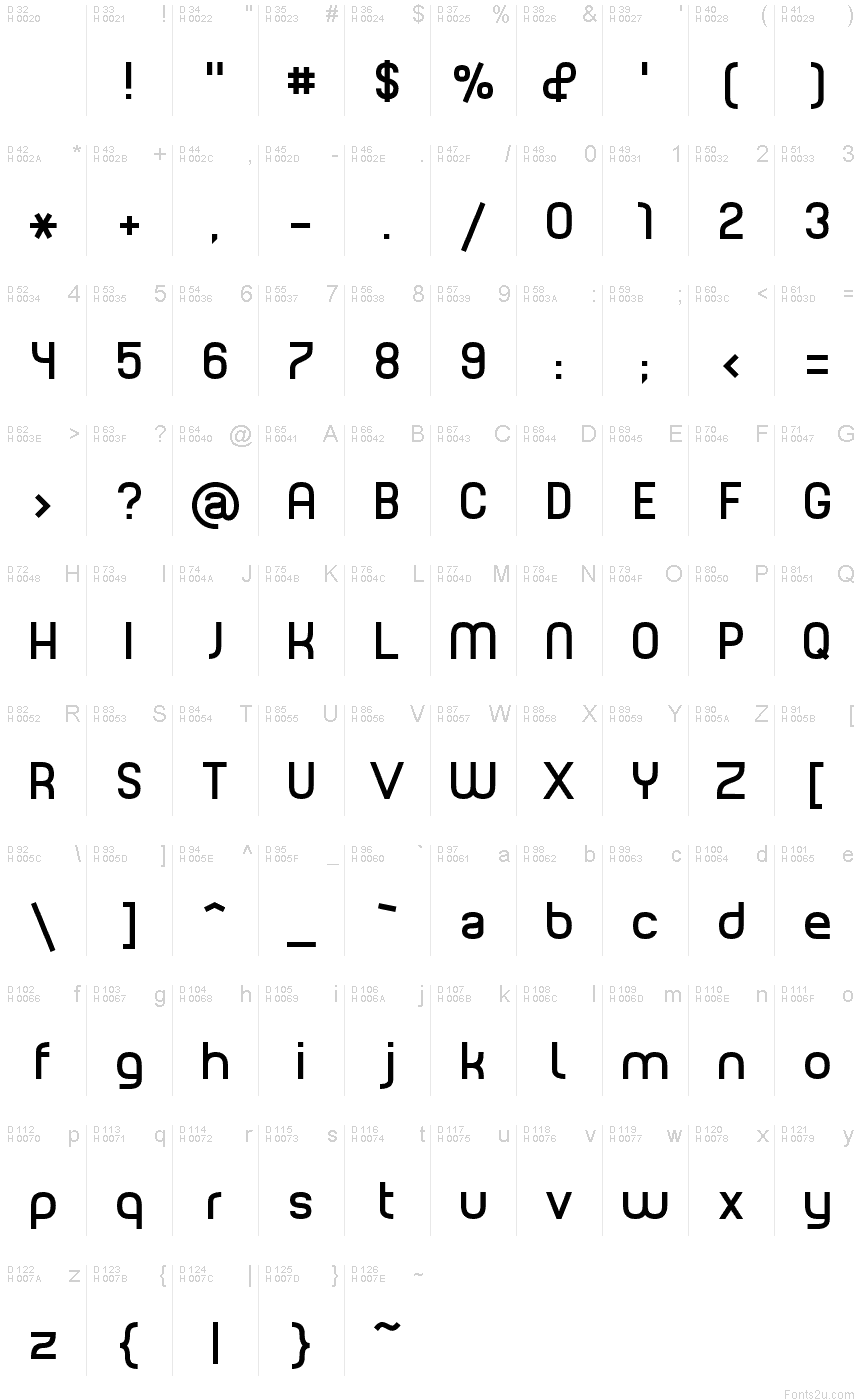
Planet Estyle من A Planet Font هو خط مجاني مستدير بلا زوائد (sans serif) يتميز بطابع تقني من أواخر التسعينيات. تمزج الحروف بين الخطوط السميكة والناعمة مع منحنيات هندسية انسيابية، بينما تمنحه الخطوط العمودية الطويلة والبسيطة مظهرًا انسيابيًا بدلاً من المظهر المرح.
يعتبر هذا الخط مناسبًا لأغلفة الموسيقى، ومنشورات النوادي، وعلامات البرمجيات التجارية، وعناوين الويب، وعناوين الملصقات، حيث يمكن لهذا الطابع المستقبلي الناعم أن يوصل الرسالة بفعالية. وباعتباره خطًا مجانيًا، فهو يعمل بشكل جيد أيضًا مع الشعارات القصيرة، وعناوين الأغلفة، وبطاقات العناوين، لأن المنحنيات العريضة والوصلات المدمجة تضفي على النصوص القصيرة إيقاعًا اصطناعيًا مميزًا.